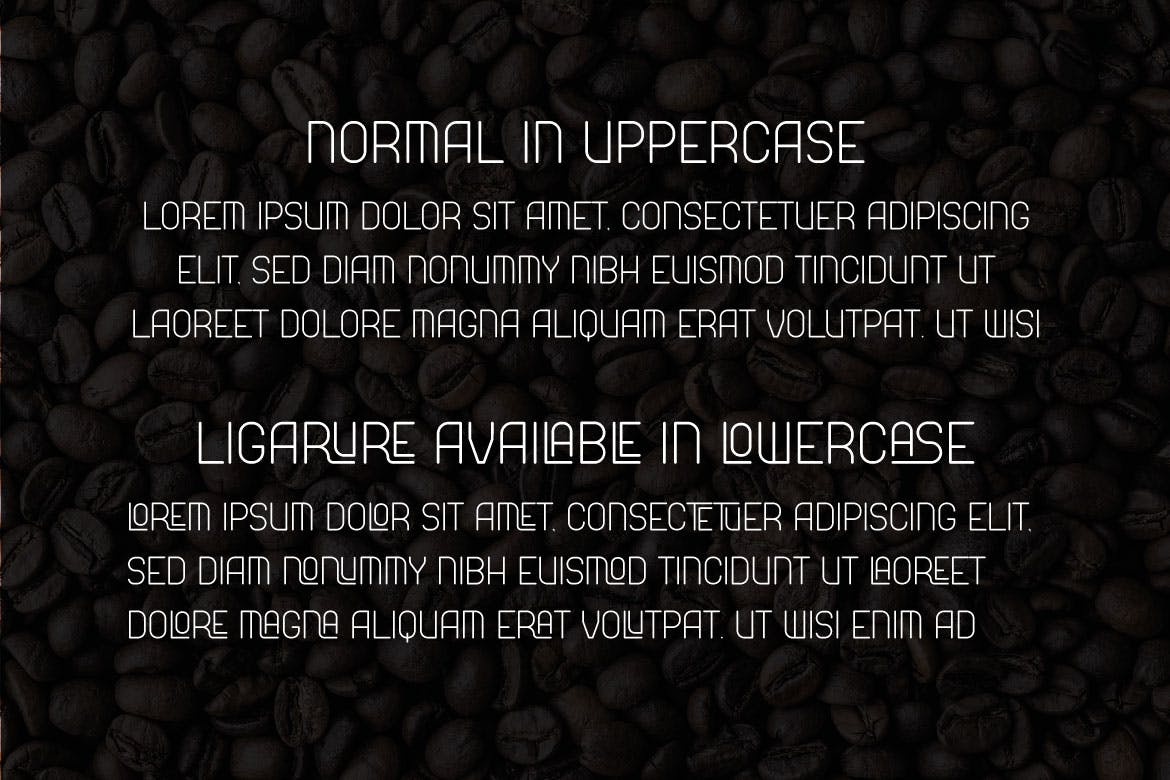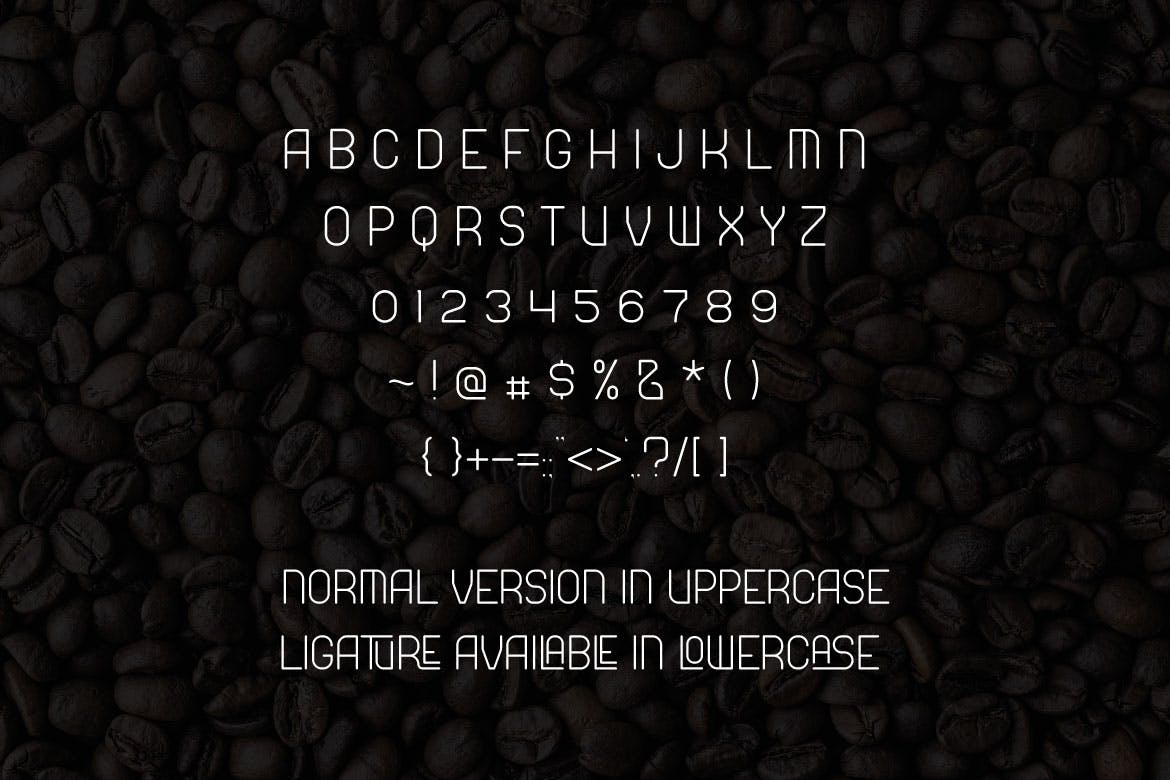
فونت ROASTER، طراحی مینیمالیستی، مدرن و شیک است که برای هر نوع کار مناسب میباشد. این فونت میتواند برای عنوانها یا محتوای متنی استفاده شود. ظاهر این فونت تمیز، مدرن و جذاب است و هرگز خستهکننده نمیشود. از این فونت در پروژههای ویرایشی، کارتهای ویزیت، کتابها، اخبار، بنرها، بروشورها، لوگو، لوازمالتحریر و بسیاری موارد دیگر استفاده کنید. همچنین، این فونت میتواند در کارهای بزرگمقیاس نیز به کار رود.
نسخه عادی فونت در حروف بزرگ و لیگاتور در حروف کوچک موجود است.